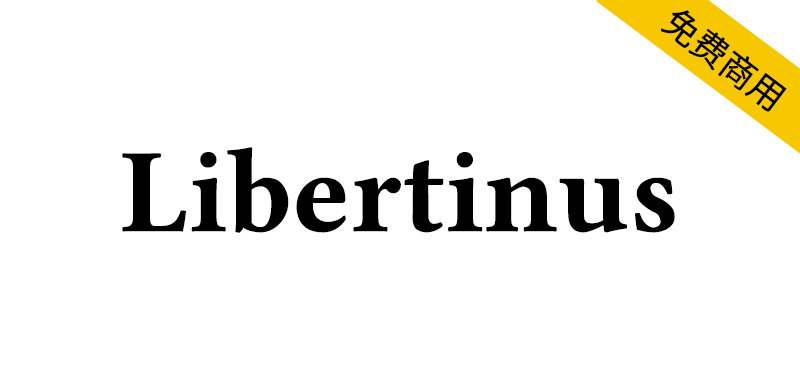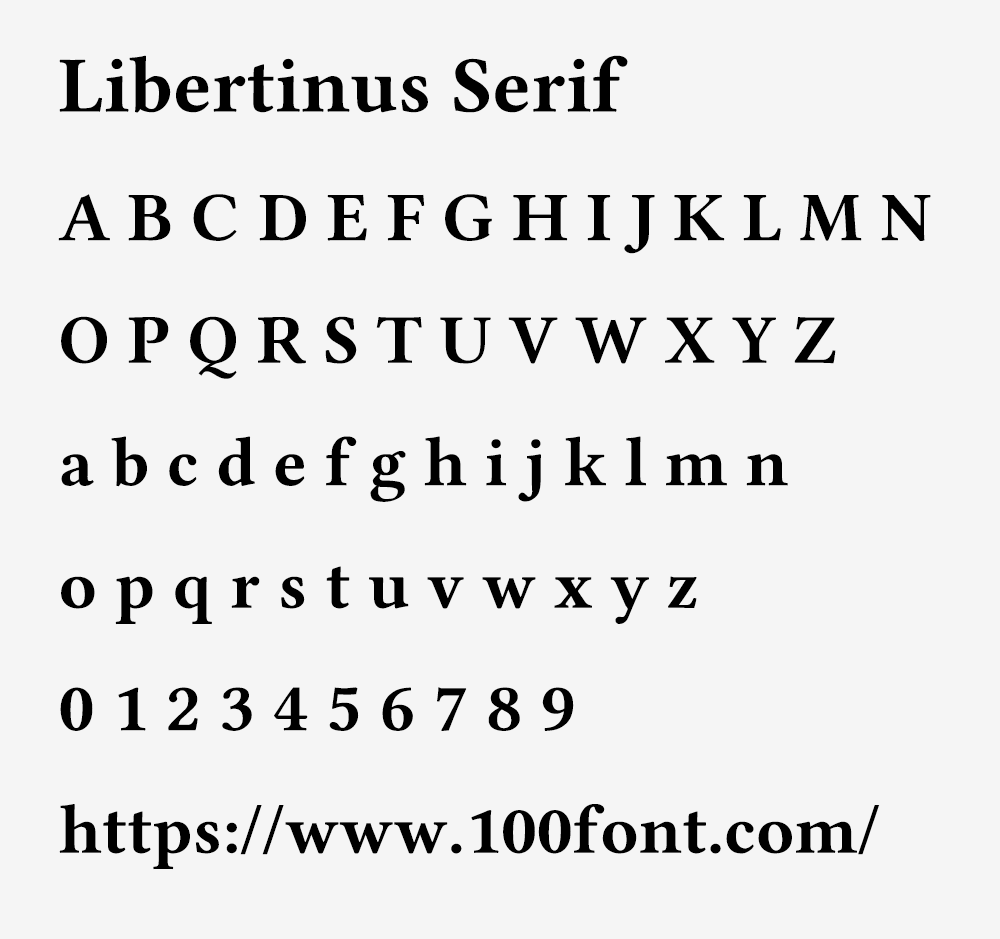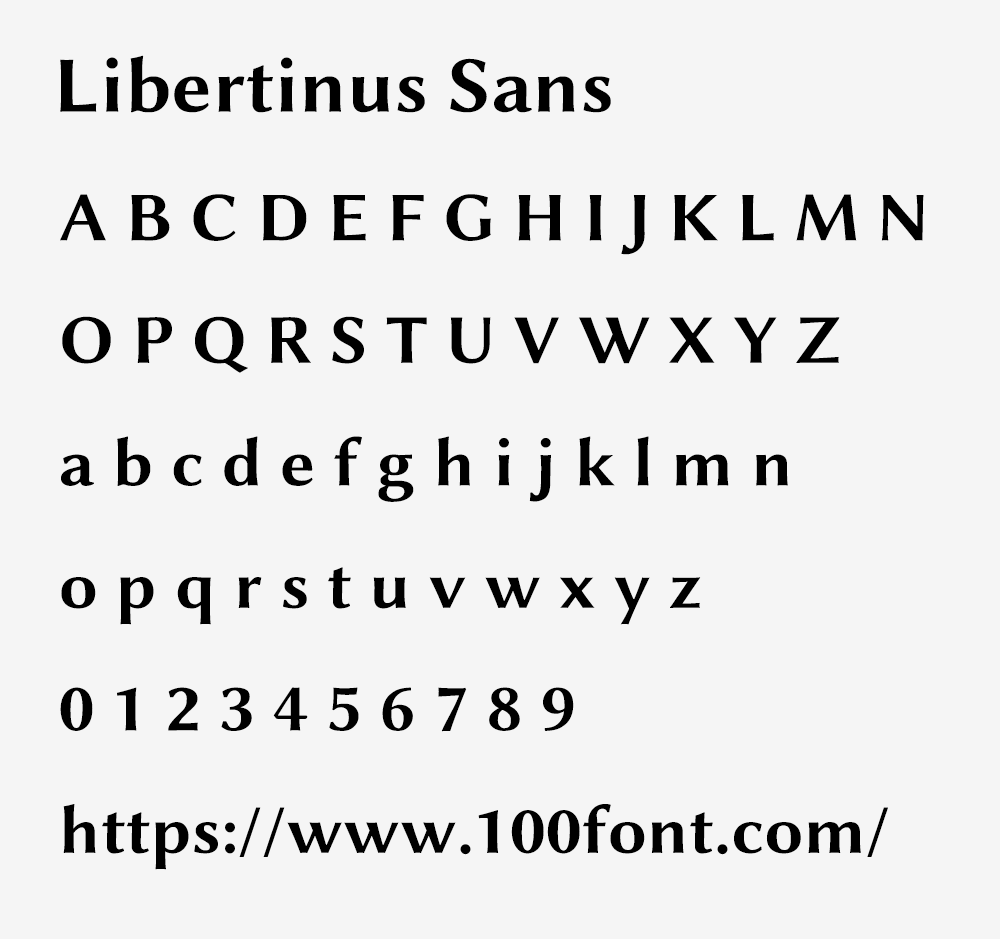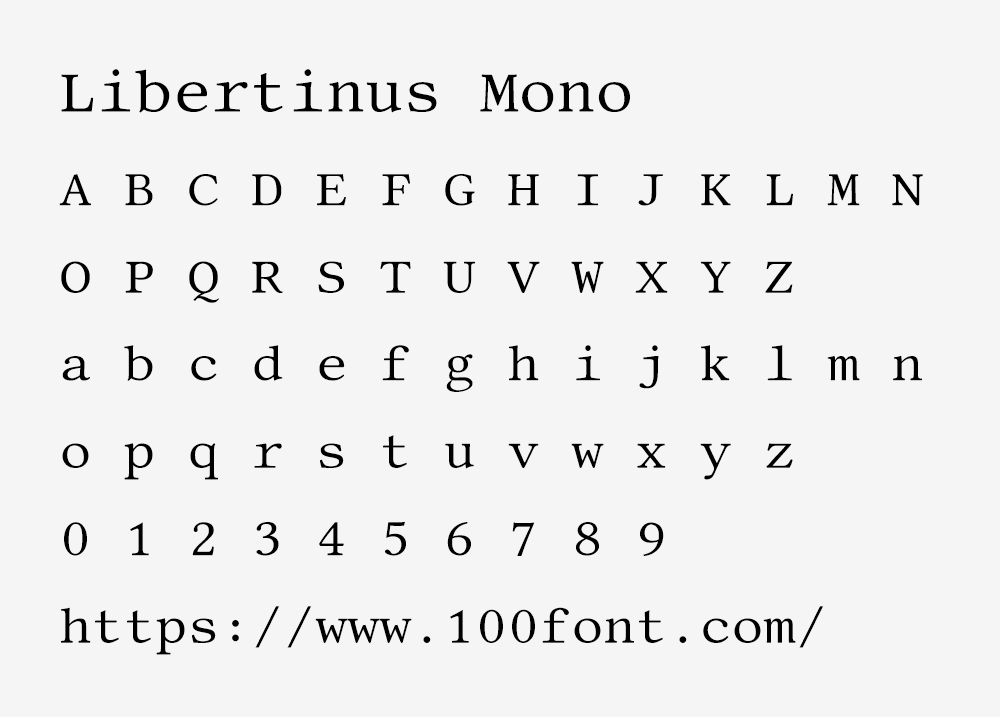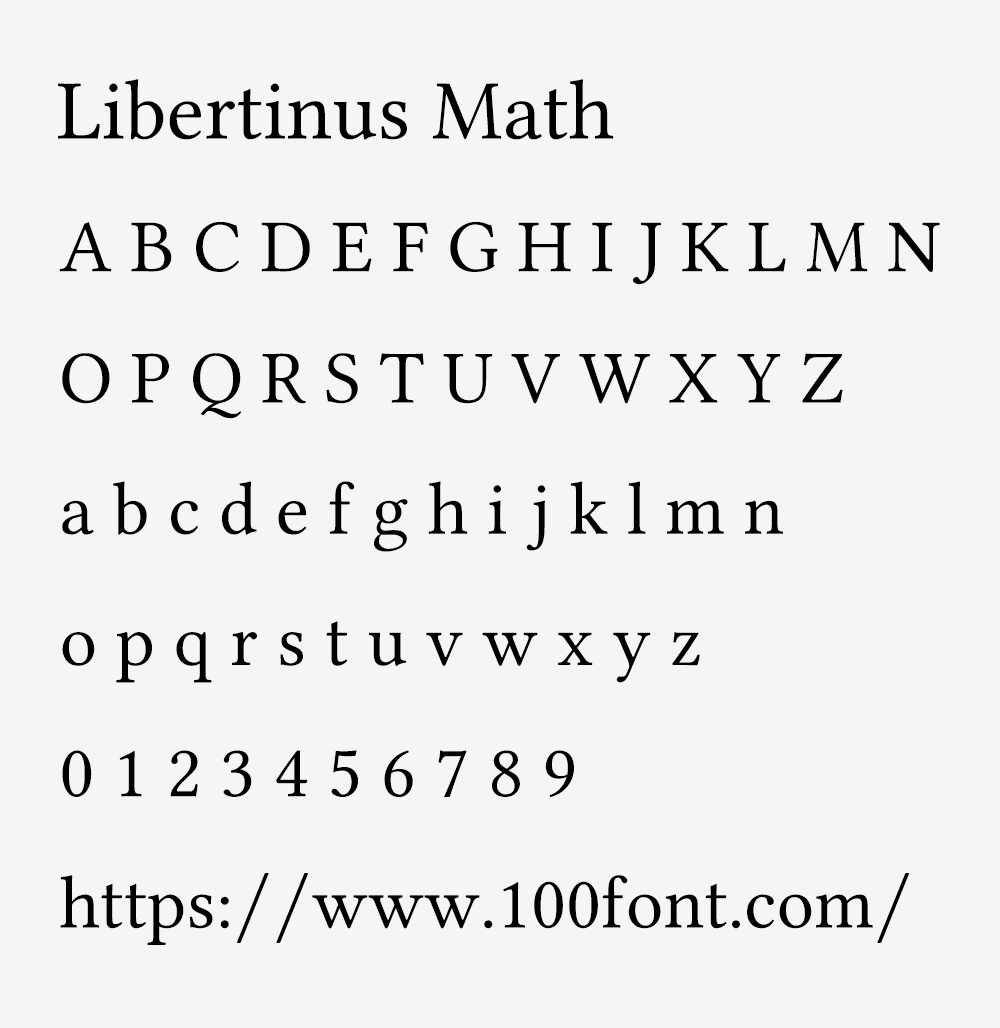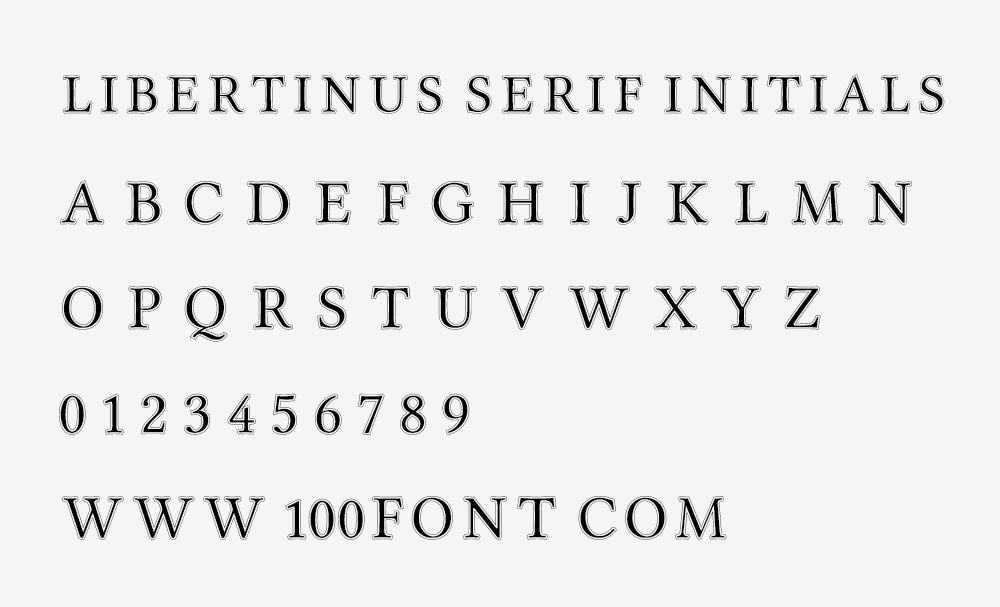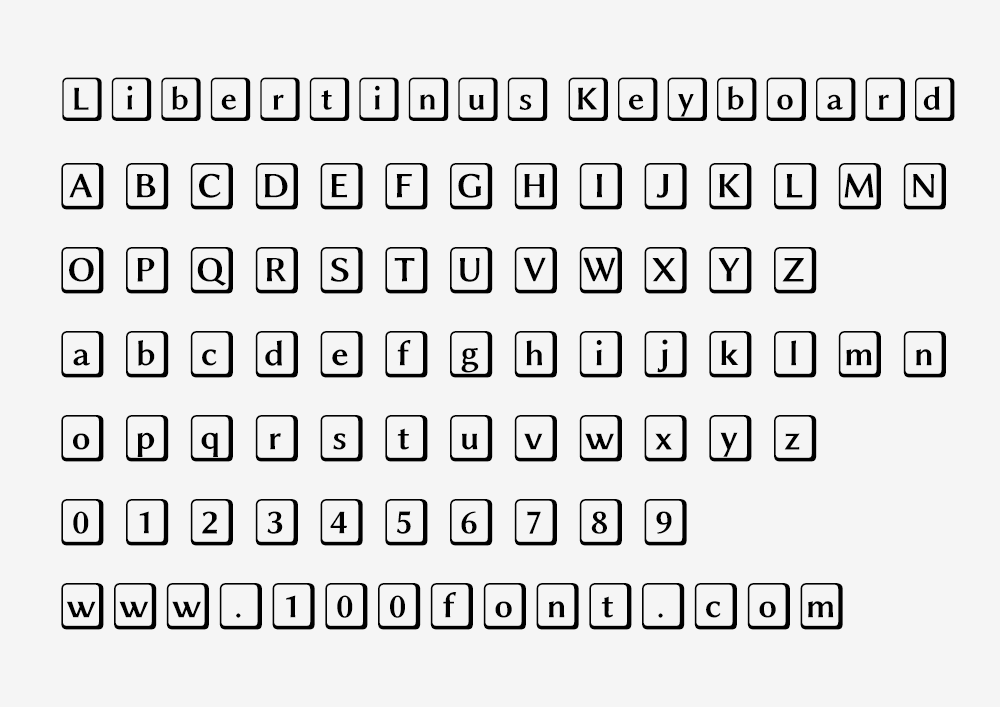
Libertinus 是一款开源的高质量字体家族,拥有四个主要字体和三个特殊用途字体,专为现代排版需求设计,尤其适合学术出版、数学公式排版以及多语言文本支持。它基于著名的 Linux Libertine 和 Linux Biolinum 字体改进而来,并增加了数学符号支持,使其成为 LaTeX、XeTeX 和 LuaTeX 等排版系统的理想选择。
Libertinus Serif(衬线字体):包含6款衬线字体,涵盖两种样式(常规体、斜体)各三种字重(常规、半粗、加粗),源自分叉项目Linux Libertine。
Libertinus Sans(无衬线字体):包含3款无衬线字体,涵盖常规体、加粗字重及斜体样式,源自分叉项目Linux Biolinum。
Libertinus Mono(等宽字体):包含1款从衬线家族衍生的等宽字体,源自分叉项目Linux Libertine Mono。
Libertinus Math(数学字体):包含1款OpenType数学字体,衍生自衬线家族并新增大量特殊符号和功能,专为支持OpenType数学排版的应用程序设计(如LuaTeX、XeTeX或MS Word 2007以上版本)。
Libertinus Serif Display(衬线展示体):基于Libertinus衬线常规体优化,专为大字号显示设计。
Libertinus Serif Initials(衬线首字母体):衍生自Libertinus衬线体,提供空心大写字母变体,适用于首字下沉等装饰用途。
Libertinus Keyboard(键盘体):衍生自Libertinus无衬线体,每个字符带有键盘键框线,适合技术文档使用。